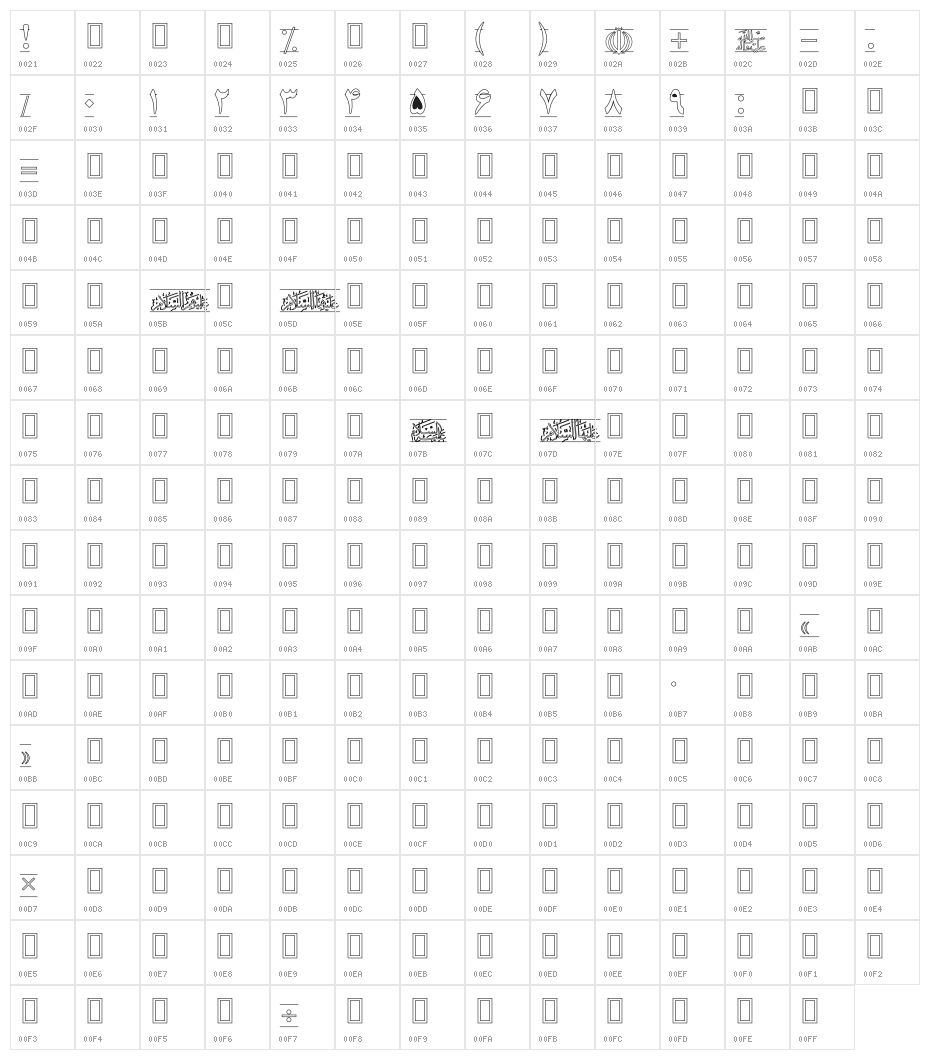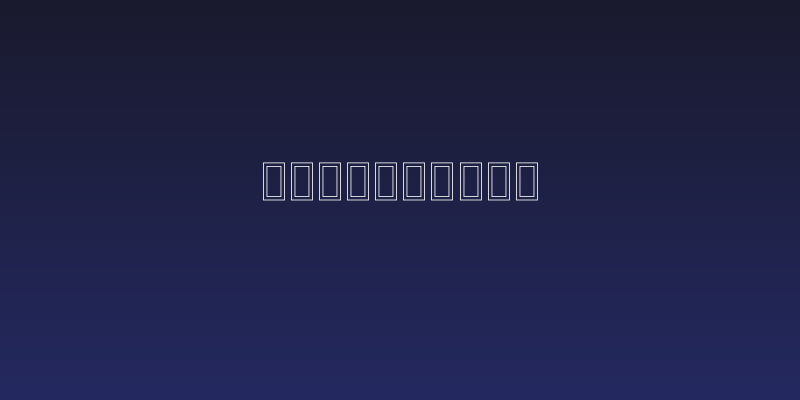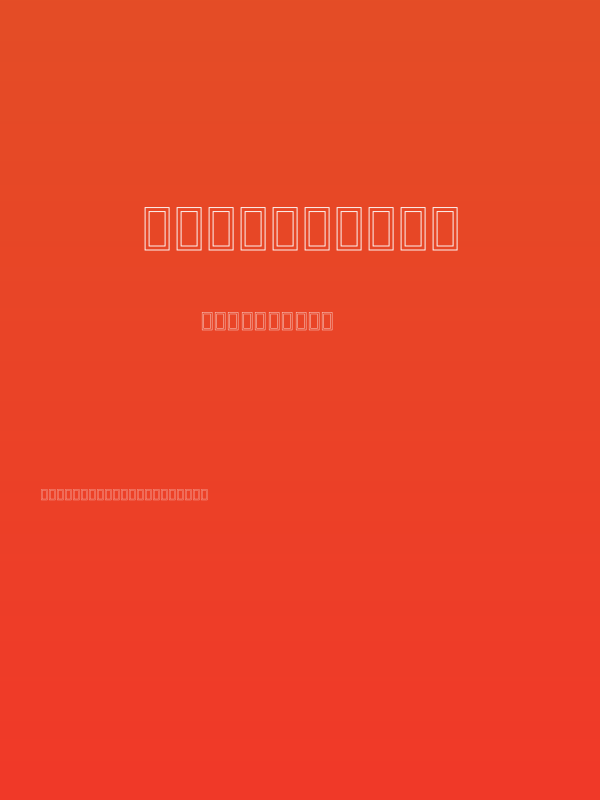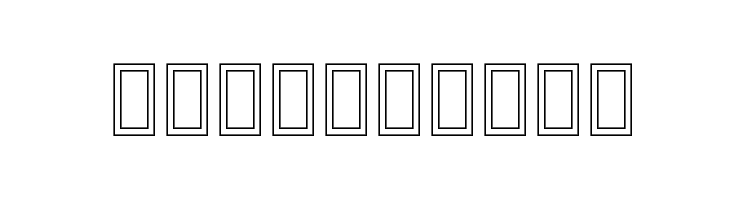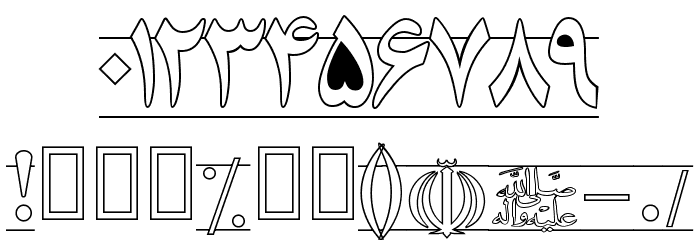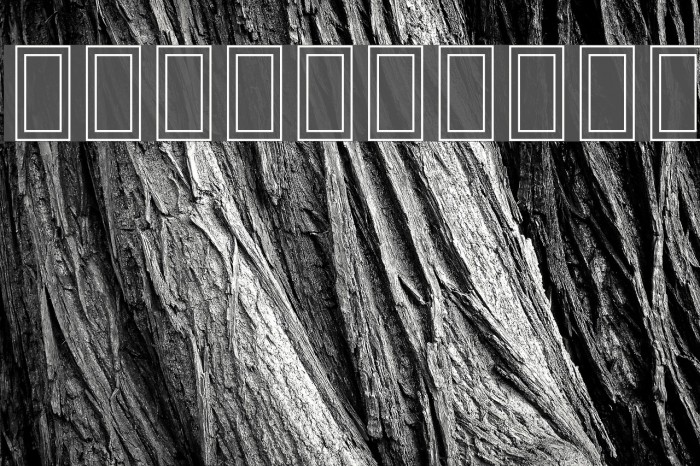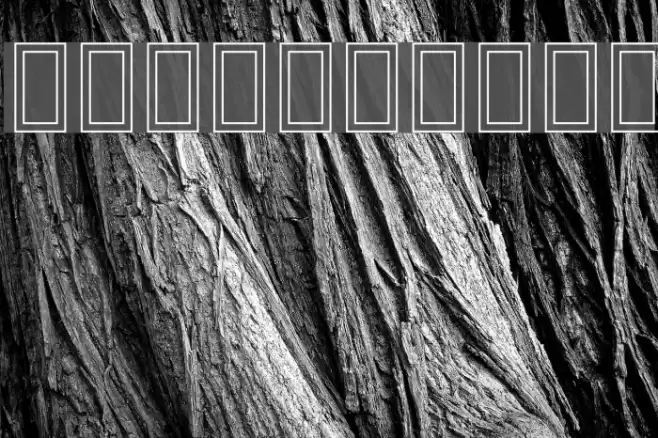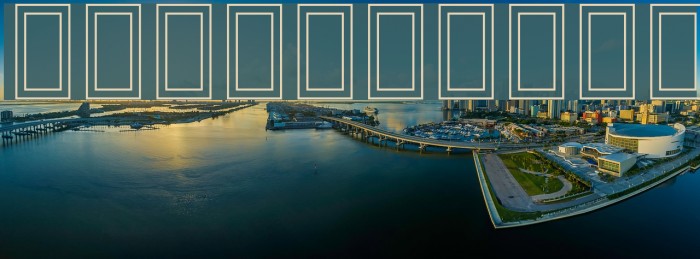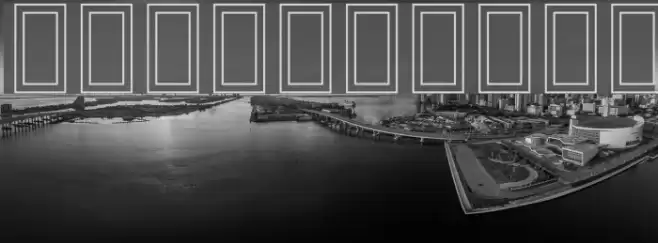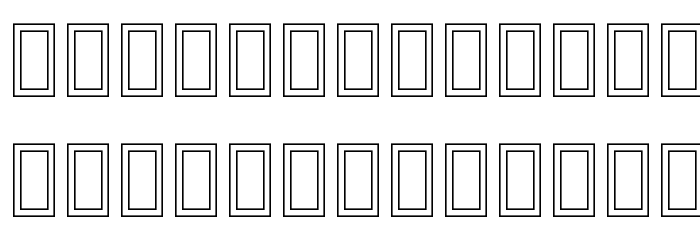
Entezaar II Font
گالری فانت فارسی پژوهش آريانا - only compatible with Farsi and Arabic
| Caso de uso | Logos, Artistic projects, Cultural event posters |
| Projetos propostos | This font is perfect for artistic projects, cultural event posters, creative branding, and any design work that seeks to incorporate a unique and decorative style. |